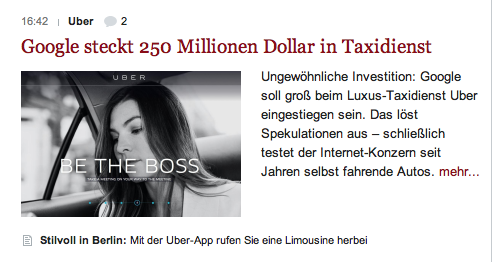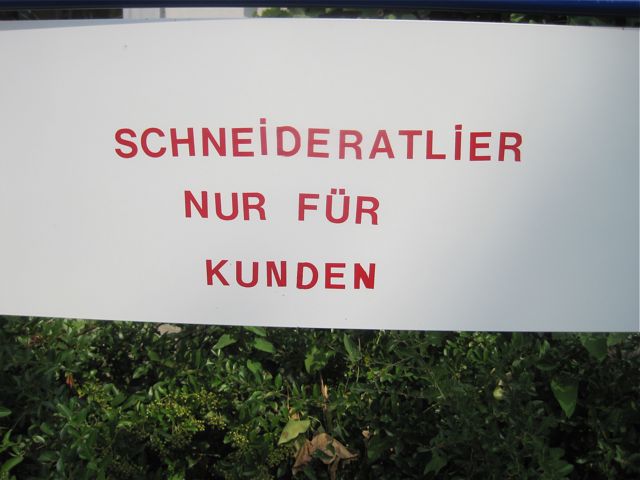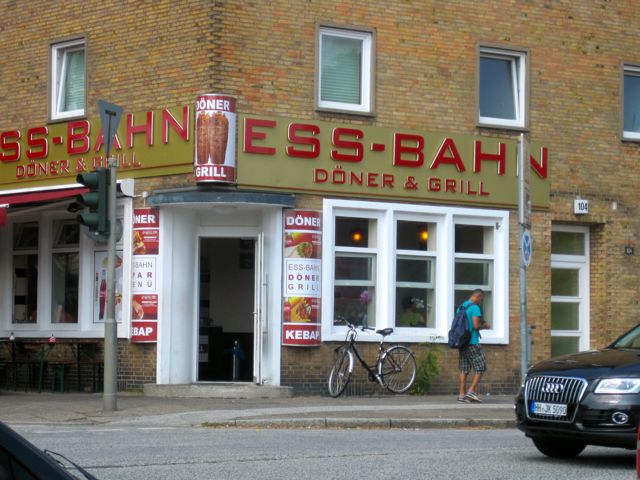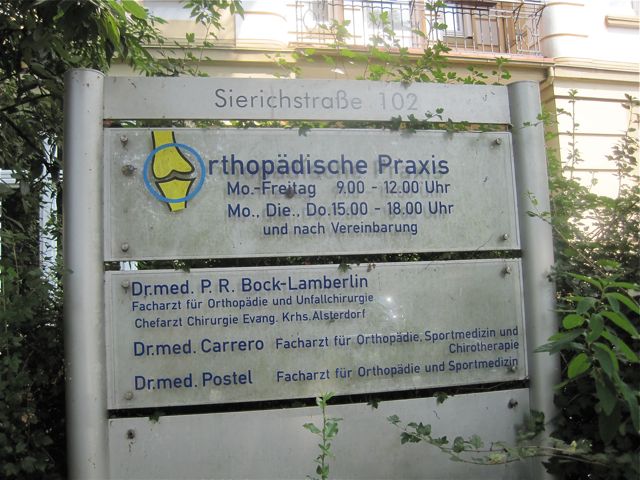
Ich verstehe den Satz so, daß man entgegen der Angewohnheit zu wirken (also zu arbeiten) lieber Mißbrauch machen soll. Bißchen holprig formuliert, das alles. Vielleicht könnte man sagen: Ehe Ihr arbeitet (und dadurch das böse System stützt), macht doch lieber irgendeinen (mißbräuchlichen) Blödsinn. Also mit anderen Worten: Arbeitslos und Spaß dabei, oder: Besinnungsloses Grundeinkommen statt Arbeit. Oder so.
Nein, nein, nein. Der Missbrauch hat sich »(ent)gegen Wirken« zu richten. So könnte man zum Beispiel Geld missbrauchen um Politiker zu bestechen, auf dass sie nicht wirken.
Ich vermute, dass "Wirken" ein politischer Gegner ist, gegen den zum Missbrauch aufgerufen wird. Wer ist dieser (oder diese) Wirken? Kann jemand den Vornamen ermitteln? Ich möchte, wenn ich schon Missbrauch mache, diesen keinesfalls gegen den Falschen richten.
Oh weh, schnell wieder zurück auf den Pfad der Typografie:
Hier ein Teil der aktuellen Schaufenstergestaltung der VR-Banken:
Und ein unorthodoxes O:
Und hier war der Änderungsschneider wohl etwas zu flink mit der Schere:
Und erinnert Ihr Euch noch an »Cef’s Back Potato«?
Das »dt« hat den Relaunch schnöde ignoriert, aber wir wollen das neue Design nicht verschweigen (auch wenn’s schwerfällt!):
Und gerade bin ich noch über dies hier gestolpert (Welt online):
Wie denn nun?  :-? Die Zweideutigkeit ist wohl ein Kind der neuen Rechtschreibung, oder?
:party:  Wo hast Du das denn ausgegraben?
Hypſch iſſes jedenfalls ...
ſ und f ſchön differenziert auch durch die Unterlänge ... Und Antiqua!
War das "am" mal eine gültige Schreibweiſe?
Das hört sich für mich nach Ruhrpottgrammatik an. »Kevin, Du kommst jetzt sofort bei die Mama!« »Wo gehts ’n hier nach Aldi?«
Richtig lange gegrübelt habe ich allerdings bei etz·. War das irgendwann mal üblich?
Richtig, da war das mal her, erinnerte mich nur leider nicht mehr. Dieses c, dass sich so leicht zum e umbauen lässt, war damals sehr beliebt. Ichg hab auch noch einige Abbildungen, wie eine GAGFA-Hausordnung in Emaile. Schön dass her noch mehr Beschriftungen des Bunkers sind, ist generell schon eine interessante Schrift, wenn auch aus schlimmer Zeit.
Nein, ich hatte dies nicht erwähnt, weil die Wiener Bunkerschrift noch ein paar mehr  Besonderheiten, wie das originelle g, ein besonderes s, die Unterlänge beim ſ und ein N bei dem der Schrägstrich ziemlich hoch endet aufweistr. Aber das zur kompletten Schrift steht auch auf meiner Liste, ich mag solche "schrägen" Details
Schone sachen, aber mit Deppen-Leerzeichen im Beschreibungstext: (zu bild 10)
...darunter Kunden wie die Reichsbahn, die Deutsche Luft Hansa AG und die Deutsche Zeppelin-Reederei. ..
Soweit ich weiß hieß die Firma immer schon Lufthansa.
Oh, da habe ich auch ein passenden Beispiel! Die Bildmarke der Hamburger Designagentur Solutions zeigt einen Greifvogel:
Dreht man das Logo um, erhält man …
… einen kleine Zauberer!
Ist das gewollt oder Zufall?